Dalam dunia desain grafis dan pengembangan web, font digital sering kali digunakan untuk menciptakan tampilan yang menarik dan kohesif. Font digital tidak hanya memengaruhi kesan visual sebuah desain, tapi juga dapat membantu mengkomunikasikan pesan yang tepat kepada audiens. Namun, sering kali menemukan font digital yang sesuai dengan kebutuhan desain bisa menjadi tugas yang menantang.
Untungnya, banyak font digital berkualitas tinggi yang dapat diunduh secara gratis, memungkinkan desainer untuk mengakses beragam pilihan tanpa harus mengeluarkan biaya tambahan. Dalam artikel ini, kami telah mengumpulkan 40 font digital terbaik yang bisa langsung Anda unduh dan gunakan secara gratis untuk meningkatkan kualitas desain Anda. Yuk, simak daftarnya di bawah ini!
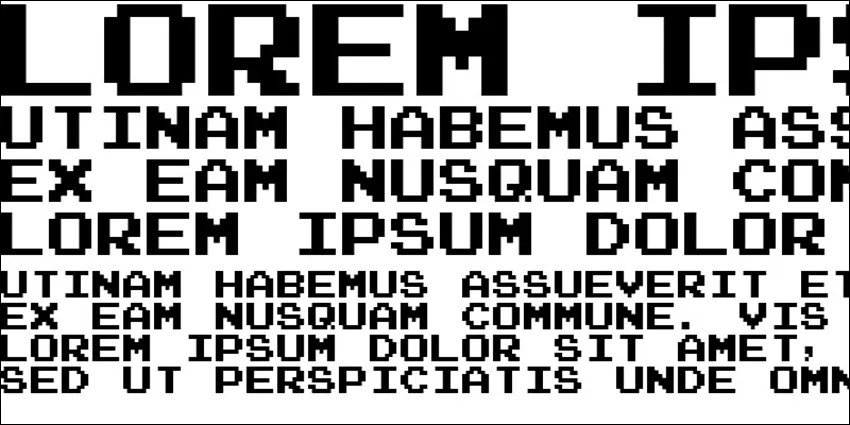
Font pertama adalah Arcade Regular, font yang menghadirkan suasana retro dari era permainan arkade, cocok digunakan untuk judul atau tajuk berita dalam desain grafis yang ingin memunculkan nuansa nostalgia.
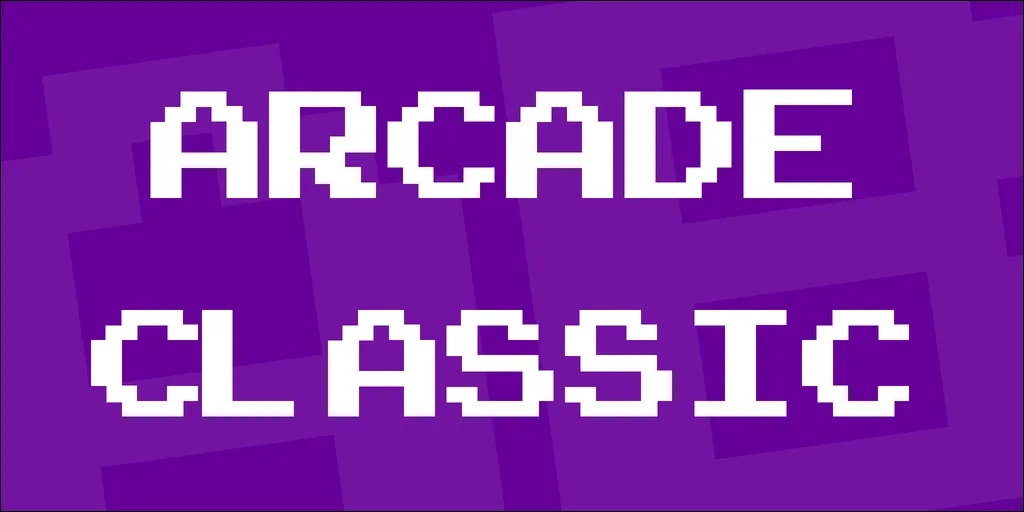
Font kedua adalah Arcade Classic, varian dari font Arcade yang menampilkan gaya tulisan yang lebih bold dengan tetap mempertahankan nuansa retro, ideal digunakan untuk teks berukuran besar seperti judul poster atau headline.
Selanjutnya adalah font Subway Ticker, font yang terinspirasi oleh tampilan papan pengumuman di stasiun kereta bawah tanah, memiliki garis-garis yang jelas dan tegas sehingga sangat cocok digunakan untuk membuat teks yang mudah terbaca pada media digital atau cetak.
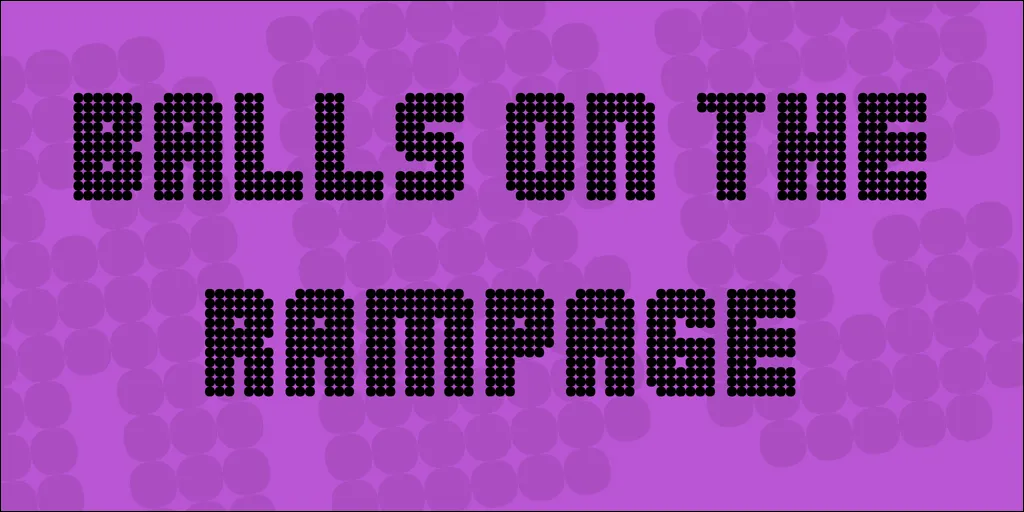
Dengan desain yang berani dan eksentrik, font ini cocok untuk desain-desain poster acara atau merchandise yang ingin menarik perhatian dengan gaya yang berbeda.
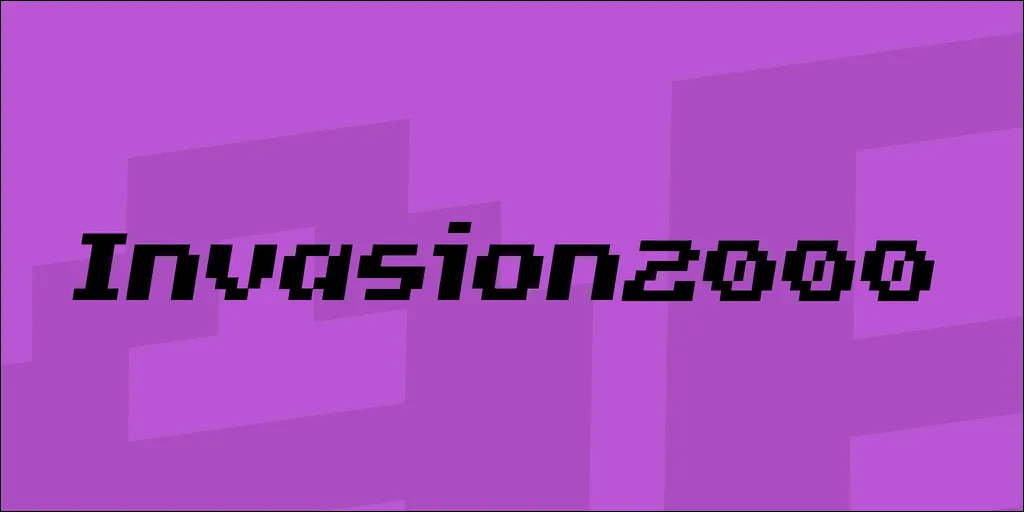
Font dengan gaya futuristik ini ideal untuk digunakan dalam poster, label produk, atau situs web.
Dengan desain yang penuh dengan titik-titik, font ini memberikan kesan modern dan kreatif, cocok untuk desain-desain yang ingin menonjolkan elemen visual dan memberi kesan yang unik seperti pada poster atau situs web.
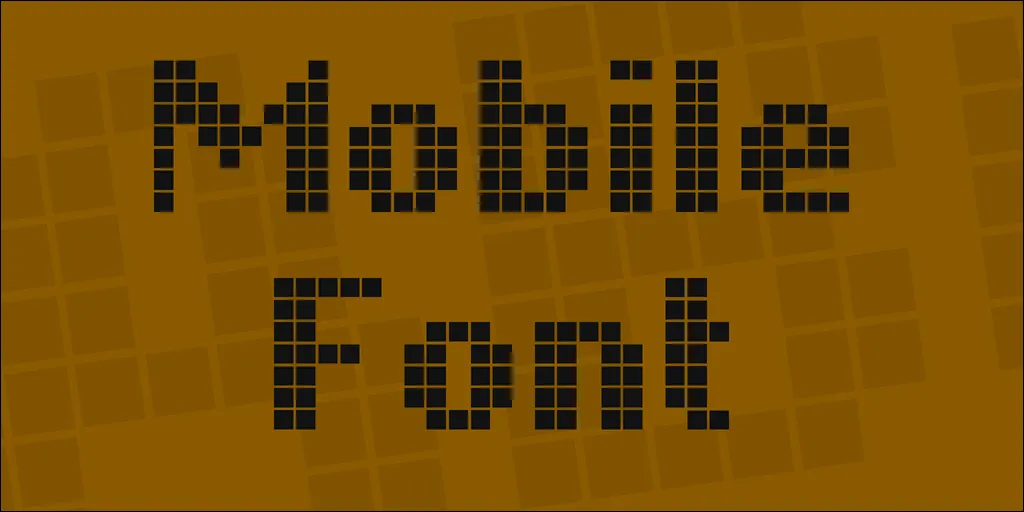
Mobile Font adalah font yang didesain khusus untuk tampilan pada perangkat mobile dengan huruf-huruf yang jelas dan mudah terbaca meskipun pada layar yang kecil, ideal digunakan untuk desain aplikasi atau situs web responsif.
Radioland Regular adalah font yang terinspirasi dari gaya tipografi radio jaman dulu dengan garis-garis yang sederhana namun kuat, cocok untuk desain-desain yang ingin menghadirkan kesan klasik dan vintage seperti pada poster, label, dan lain-lain.
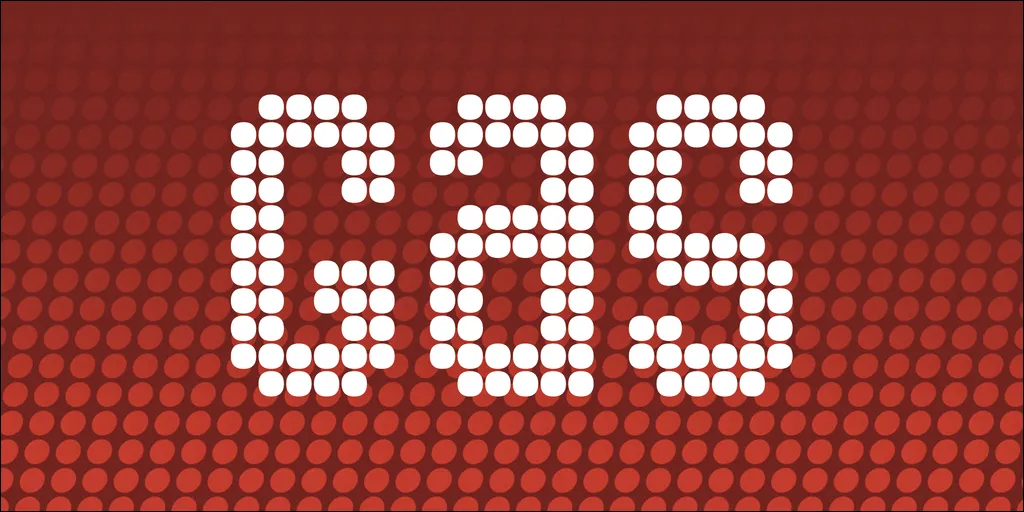
Dengan desain yang sederhana dan bersih, font ini cocok untuk desain-desain yang ingin memberikan kesan minimalis dan modern seperti pada label produk atau situs web yang ingin menonjolkan kejelasan dan keterbacaan.
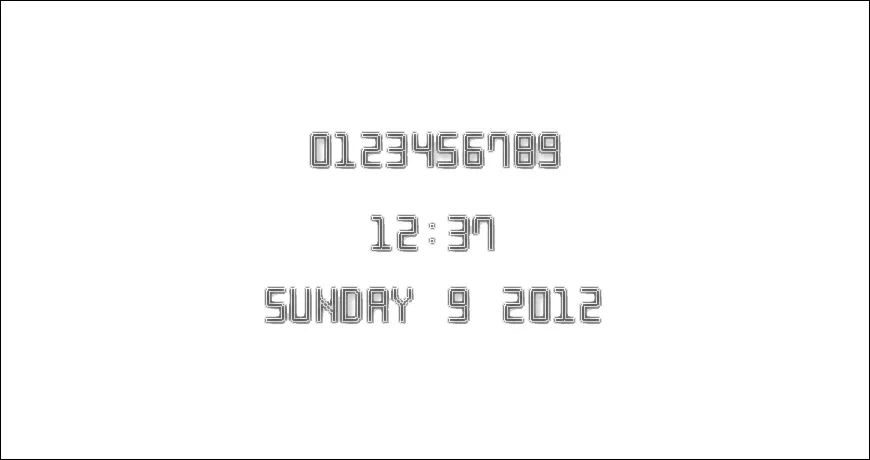
Dengan sentuhan neon yang mencolok, font ini cocok untuk desain-desain yang ingin menampilkan kesan futuristik dan energik seperti pada poster acara atau merchandise.
Dot Digital-7 memiliki tampilan layar digital dengan pola titik-titik yang teratur, cocok digunakan untuk desain-desain yang ingin menampilkan kesan yang modern, seperti pada poster, situs web, dan lain sebagainya.
Font ini memiliki desain yang bersih dan modern dengan proporsi huruf yang pas, cocok digunakan untuk desain-desain yang mengutamakan keterbacaan tinggi seperti pada tampilan teks di situs web atau aplikasi yang ingin memberikan pengalaman pengguna yang optimal.
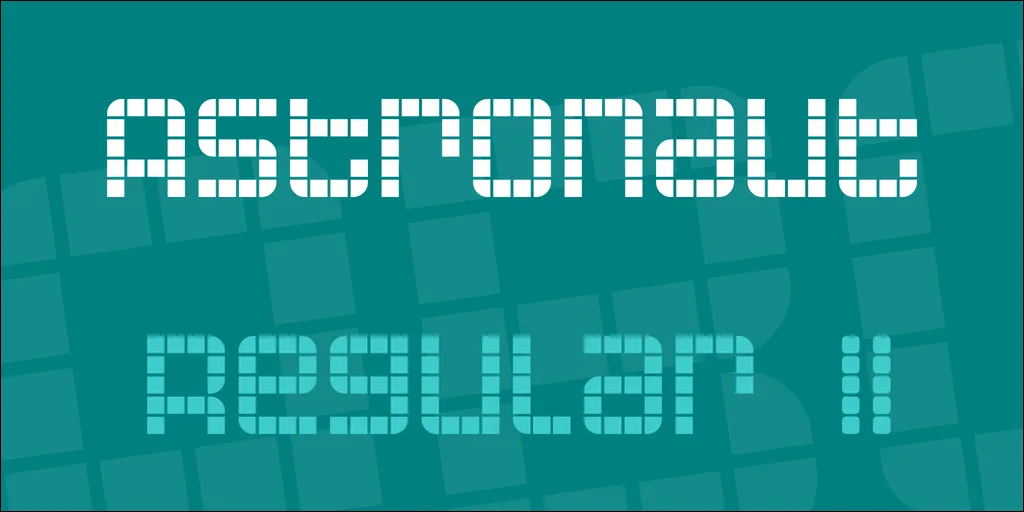
Astronaut Regular adalah font dengan desain yang futuristik dan berdimensi, menghadirkan kesan ruang angkasa yang eksploratif, cocok digunakan untuk desain-desain poster atau merchandise yang ingin menonjolkan elemen visual yang unik.
Anticlimax adalah font techno dengan desain kotak yang unik dengan detail-detail yang eksentrik, cocok digunakan untuk poster, label, logo, header situs web, dan lain-lain.
Font ini tampil dengan sentuhan neon retro yang futuristik dan segar, cocok untuk desain-desain yang ingin menampilkan kesan modern dan energik seperti pada poster acara, logo, label, hingga merchandise.
Oxygene 1 adalah font digital dengan desain yang unik dan berani, cocok digunakan untuk desain-desain grafis.
ComputerAmok adalah font yang terinspirasi dari tampilan layar komputer dengan huruf-huruf yang berdesakan dan teratur, cocok digunakan untuk desain-desain yang ingin menampilkan kesan yang modern, seperti headline poster, label, dan proyek desain grafis lainnya.
Ukuran font yang tepat tergantung pada faktor-faktor seperti jenis desain, konten yang akan ditampilkan, dan platform penggunaannya. Sebagai aturan umum, penting untuk memastikan bahwa teks tetap mudah dibaca tanpa perlu zooming atau cropping.